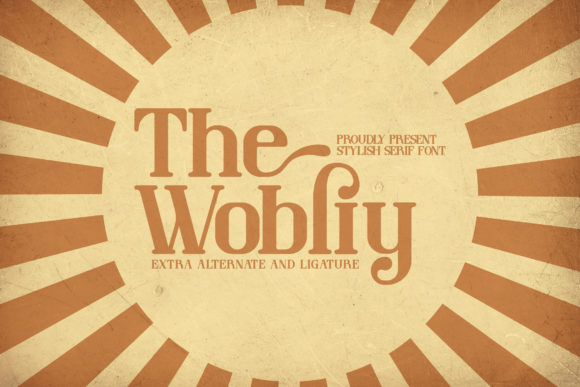
Название: The Wobliy Font (2022)
Wobliy - это стильный шрифт с засечками, который имеет свой собственный уникальный стиль и современный вид.
Этот шрифт идеально подходит для элегантного и роскошного логотипа, дизайна названия книги или фильма, модного бренда, журнала, одежды, надписей, цитат и многого другого.
Название: The Wobliy Font (2022)
Wobliy - это стильный шрифт с засечками, который имеет свой собственный уникальный стиль и современный вид.
Этот шрифт идеально подходит для элегантного и роскошного логотипа, дизайна названия книги или фильма, модного бренда, журнала, одежды, надписей, цитат и многого другого.